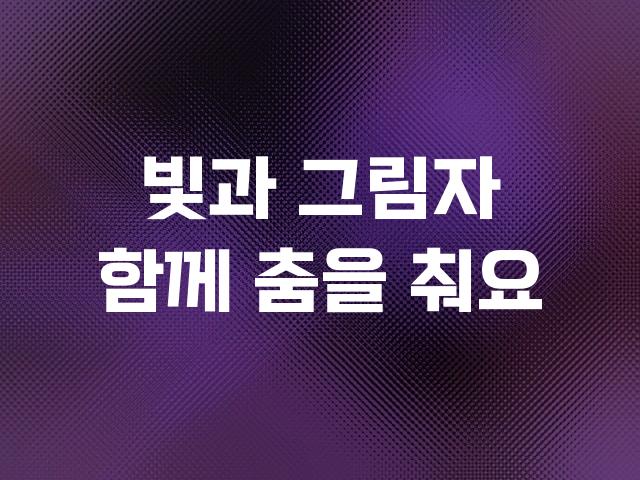
KOHI나눔은 한국보건복지인력개발원에서 제작한 기본 고딕 폰트로, 세련되고 깔끔한 디자인이 특징입니다. 이 폰트는 모던하면서도 기능적인 감성을 담고 있어 다양한 매체에서 활용 가능합니다.
기본 고딕, 감성적인, 부드러움 계열의 생김새를 가지고 있으며
웹/앱 디자인, 보고서/문서, 출판물 제목 등에서 자주 활용되며, 효과적인 메시지 전달에 적합합니다.
이 폰트는 교육, 출판/미디어, 금융/비즈니스 분야에 잘 어울리며,
신뢰감, 명확한, 전문적인 느낌을 담고 있는 것이 특징입니다.